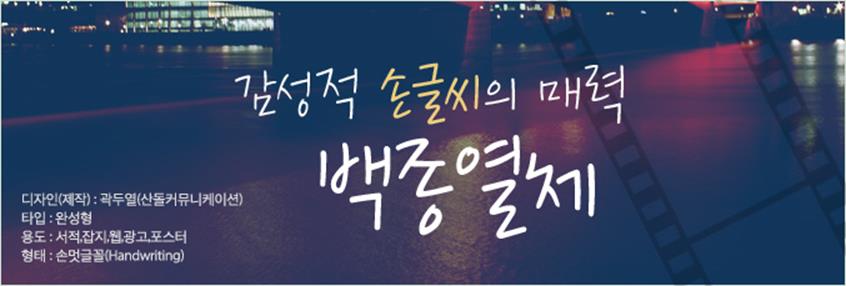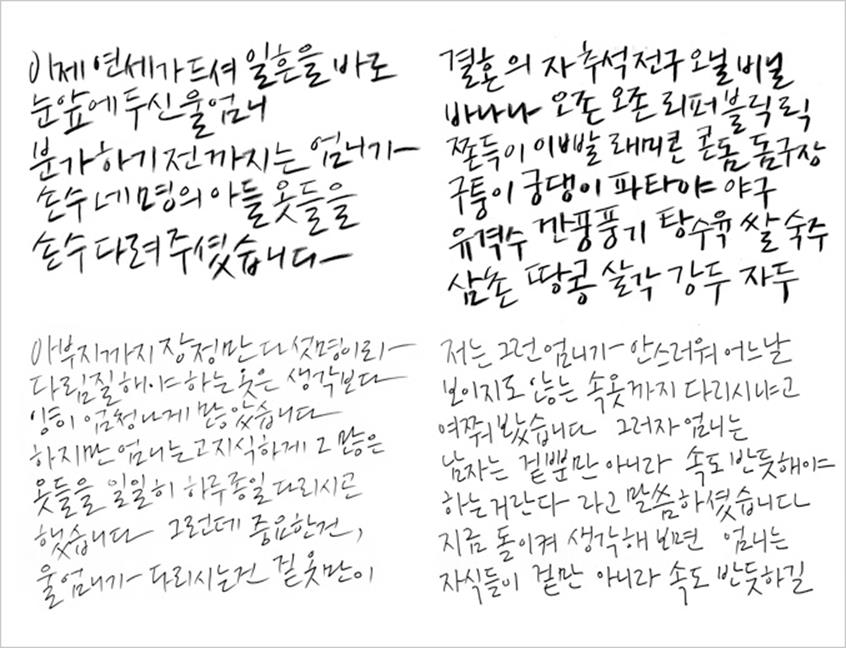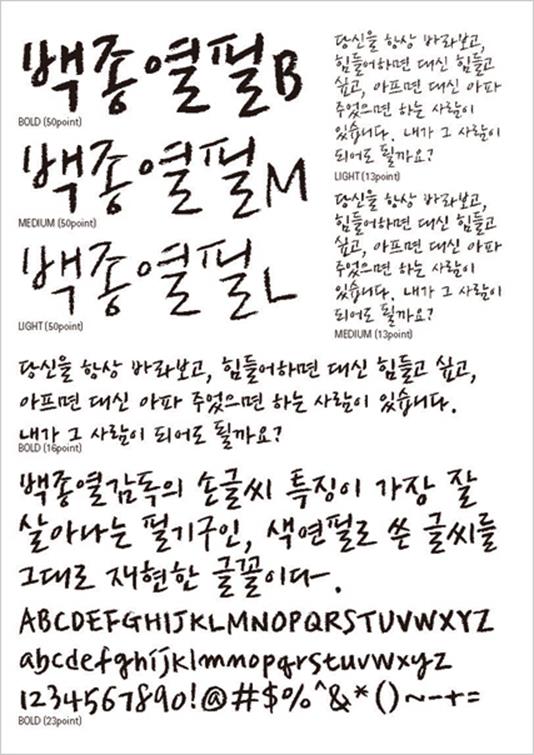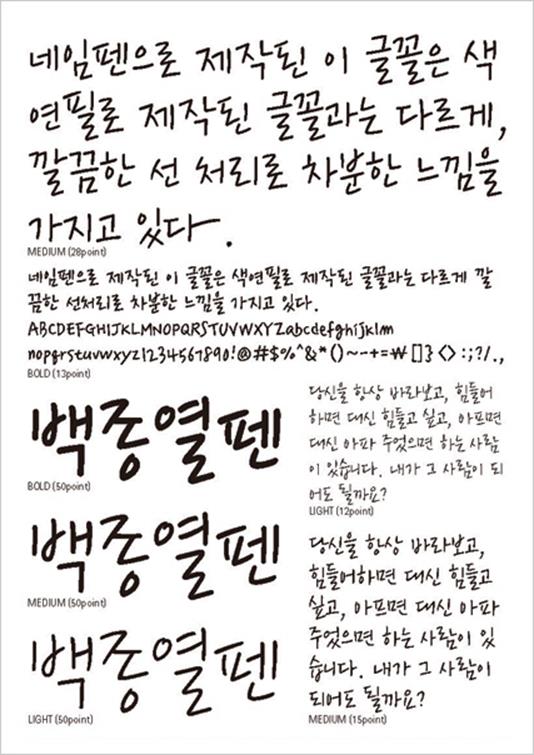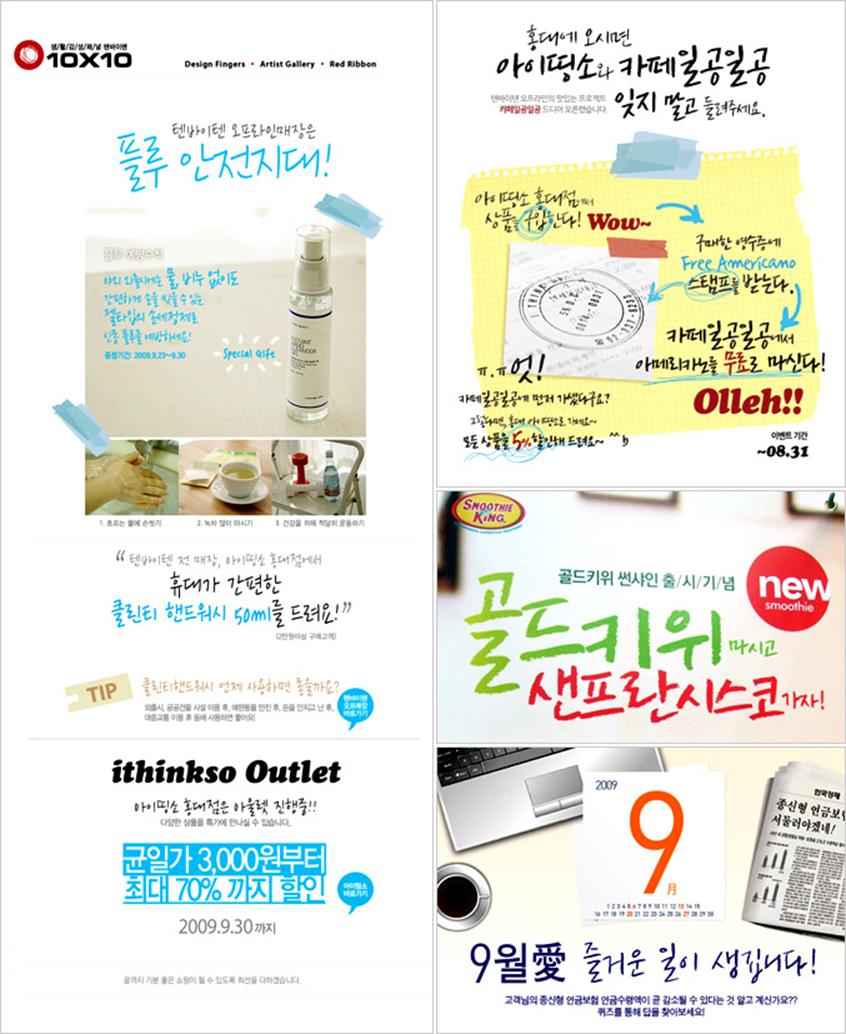
감성적 손글씨의 매력_백종열체
산돌커뮤니케이션 아티스트 컬렉션 시리즈를 대표하는 백종열체를 소개한다. 백종열체는 다수의 유명 CF에서 감성적인 손글씨로 이목을 끌었던 백종열 감독의 손글씨를 직접 폰트화한 것으로 백 감독이 직접 쓴 원도를 바탕으로 제작된 손멋글꼴이다.
▲ CF속 백종열 감독의 손글씨들
사전조사에서 폰트출시까지 총 1년 6개월이라는 장기간 프로젝트였던 백종열체는 기계적이지 않고 자연스러운 백 감독의 손글씨 원본 느낌을 그대로 살린 감성적인 매력이 고스란히 드러나는 것이 특징이다. 또한 시각기준선을 중심에 배치하여 한 층 안정감을 가져다 준다.
▲ 백종열체 제작 중 작업한 샘플이미지
▲ 백종열필 서체견본
▲ 백종열펜 서체견본
백종열체는 필체와 펜체 두 가지로 구성된다. 두 폰트의 느낌은 필기구가 표현하는 느낌에 따라 서로 다른 분위기를 불러 일으킨다. 필체는 색연필로 쓴 글씨를 재현한 것으로 색연필이 가진 거친 질감과 감성적 느낌이 폰트에서도 그대로 이어진다. 질감을 살릴수록 폰트가 무거워 지는 단점을 보완하여 활용함에 있어 부담을 덜어준다. 네임펜으로 제작된 펜체는 깔끔한 선처리로 차분한 느낌과 함께 아기자기한 느낌까지 덧붙여 표현된다.
▲ 백종열체 활용 사례 이미지